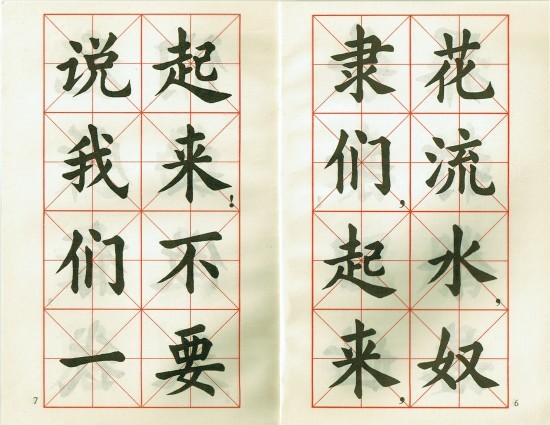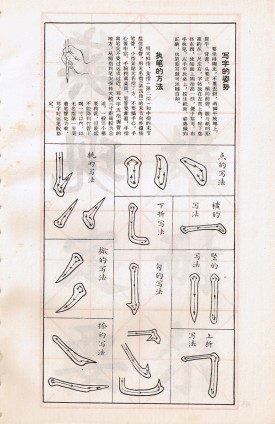
2008-06-17 中文の古本を眺める(3)『大楷字帖』 中文 書 3冊目は、上海書画社出版の『大楷字帖』。1972年9月発行、定価0.12元。下の画像にあるように、ごく普通の楷書の手本。……なのだが、内容がインターナショナルの歌詞。国际歌 (瞿秋白) - Wikisourceマスの右下に、小さく句読点【,。!?】が添えられている。字は簡体。 一番最後のページには、運筆の簡単な解説がついている。これだけでわかるのか?という気もするが。